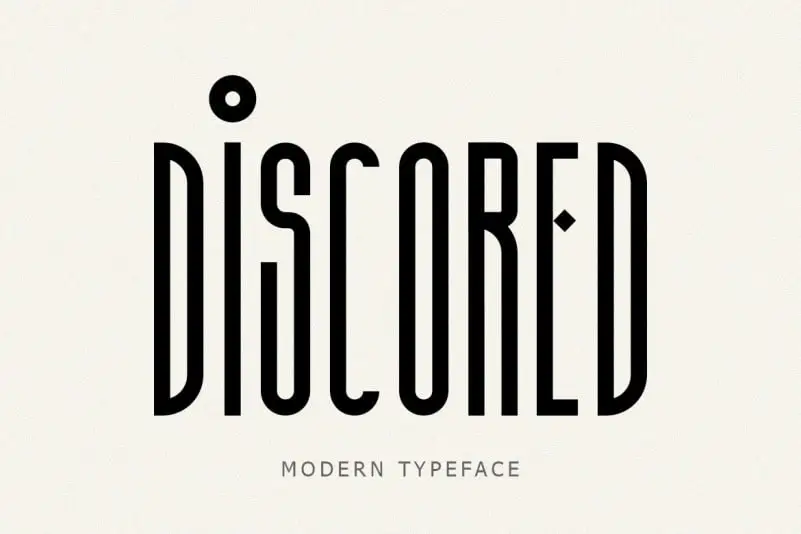
Discored Display Font – Download Grátis
A Discored Display Font é uma fonte sans-serif inspirada na arte de pintar sinais dos anos 60. Criada pelo designer Lyth Creative, essa tipografia moderna e elegante é perfeita para criar identidades visuais atraentes, desde marcas icônicas até cartões de casamento, camisetas personalizadas, assinaturas profissionais ou adesivos de prédio. Suas linhas retas e clean são ideais para criações que exigem um design minimalista, mas com um toque sofisticado. É uma ótima escolha para qualquer projeto onde você deseja destacar a estética moderna em seu design. Englobe sua identidade visual com essa fonte atemporal e de alta qualidade.